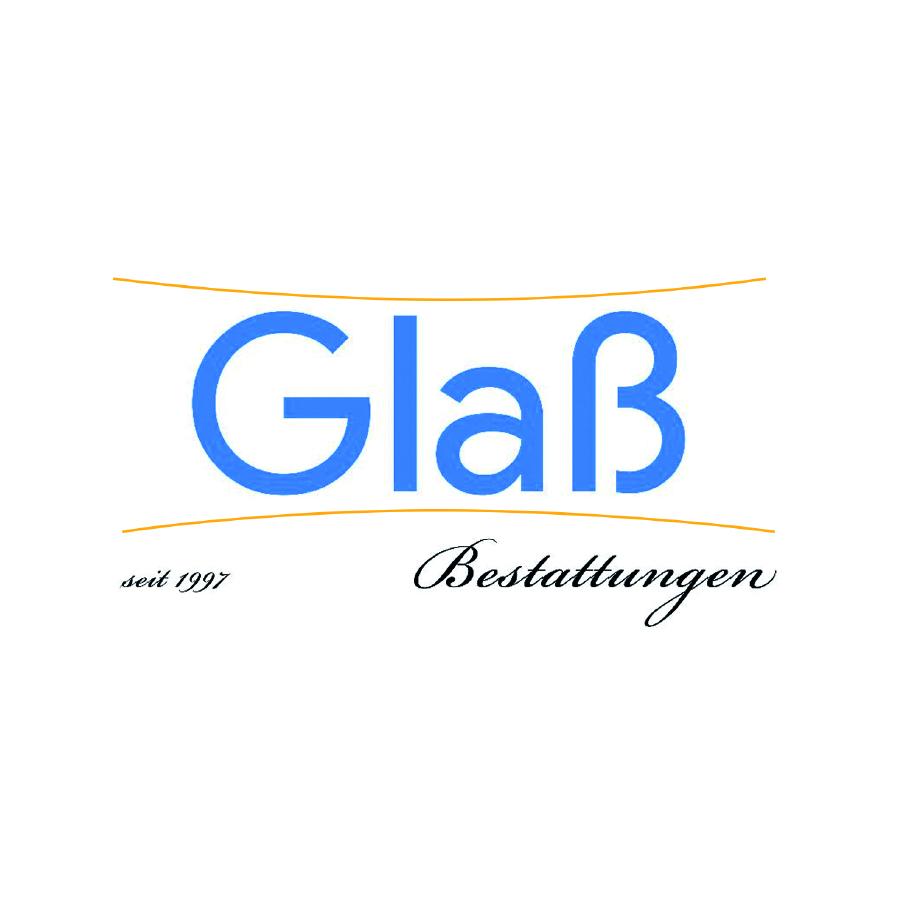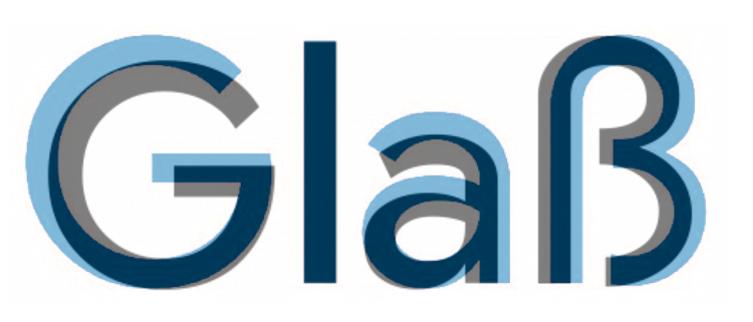
Suche Schriftart von "Glaß"
kennt jemand die beiden Schriftarten der Beispielgrafik im Anhang?
Es ist leider etwas verpixelt.
sieht aus wie die Futura, hat aber ein doppeltstöckiges a bei den Aufrechten?
Schriftname: Renner*
Designer/Publisher: indestructible type
Das ist aber nicht die Renner – in blau die gesuchte, in grau die Renner darübergelegt, "l" deckungsgleich:
@bertel: Es ist Teil eines Logos von einer kleinen Bestattungsfirma in 86666 Burgheim (Bayern).